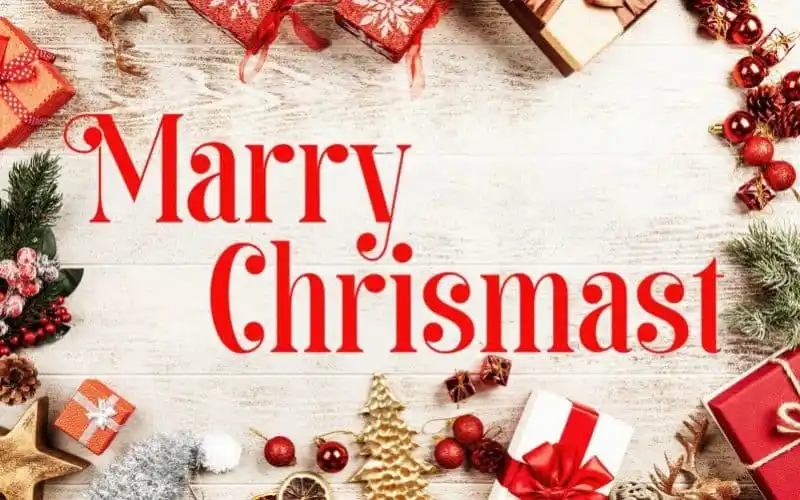
A Balinesse Serif é uma fonte serif bold com alta contraste, oferecendo versatilidade e elegância ao seu projeto. Ela traz um toque vintage para dar um visual alegre e moderno para headlines, convites, anúncios e muito mais. A fonte foi criada e compartilhada por DNArtDesign. Esta ligação de serif é uma fonte tipo contrastante, com ligatura extra e gírias alternativas. Ela suporta múltiplas línguas, incluindo letras maiúsculas, minúsculas, números e pontuação. Perfeita para iluminar seu próximo projeto, a Balinesse oferece uma combinação única de sofisticação e modernidade, tornando-a perfeita tanto para uso em projetos profissionais quanto para design gráfico criativo. Experimente essa fonte elegante e invista em sua próxima peça tipográfica com estilo Balinesse!